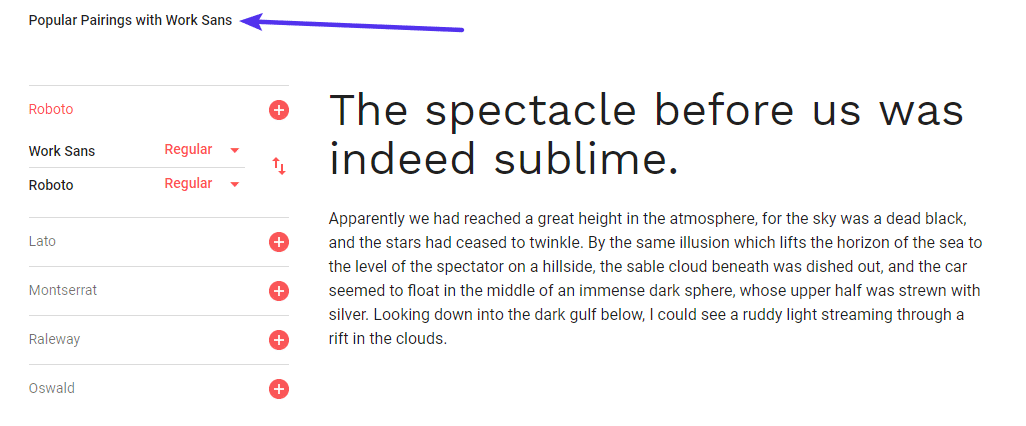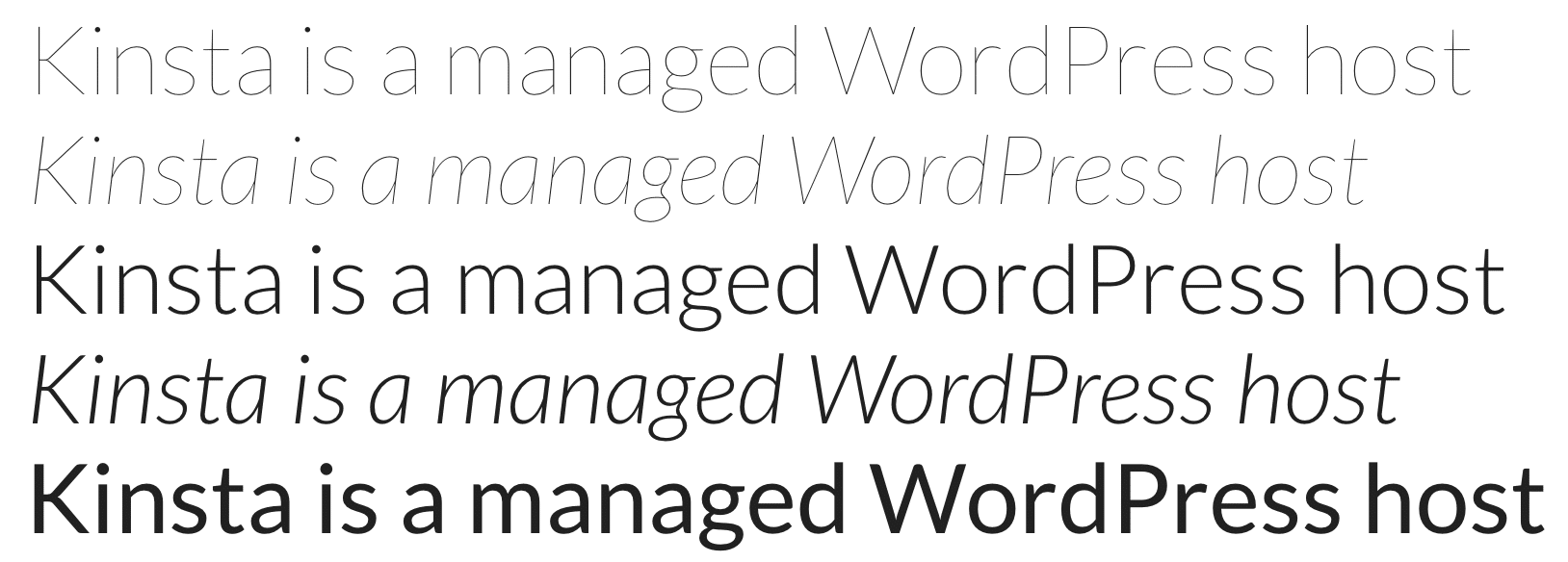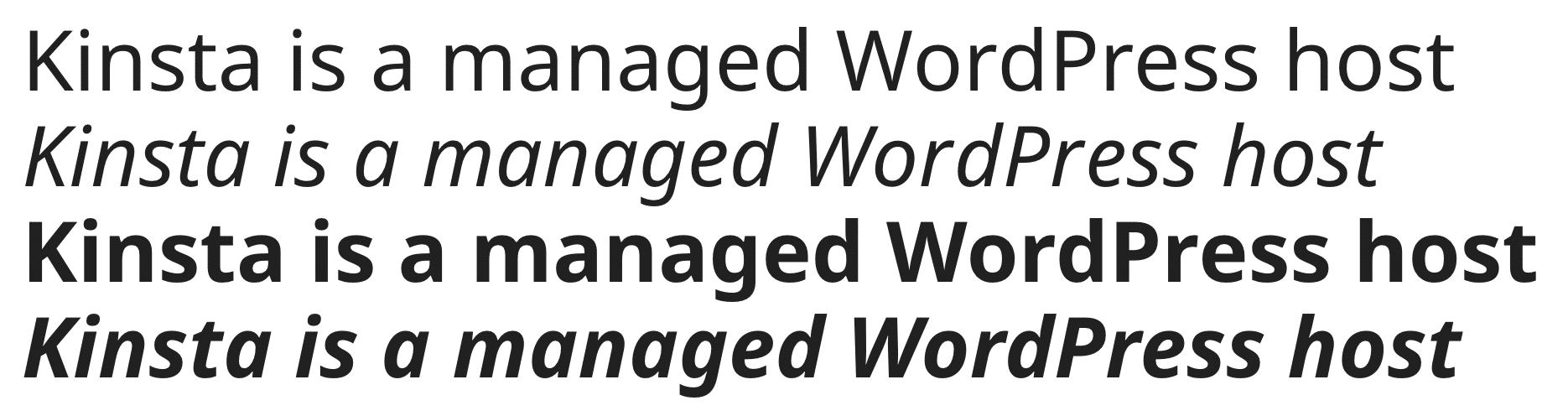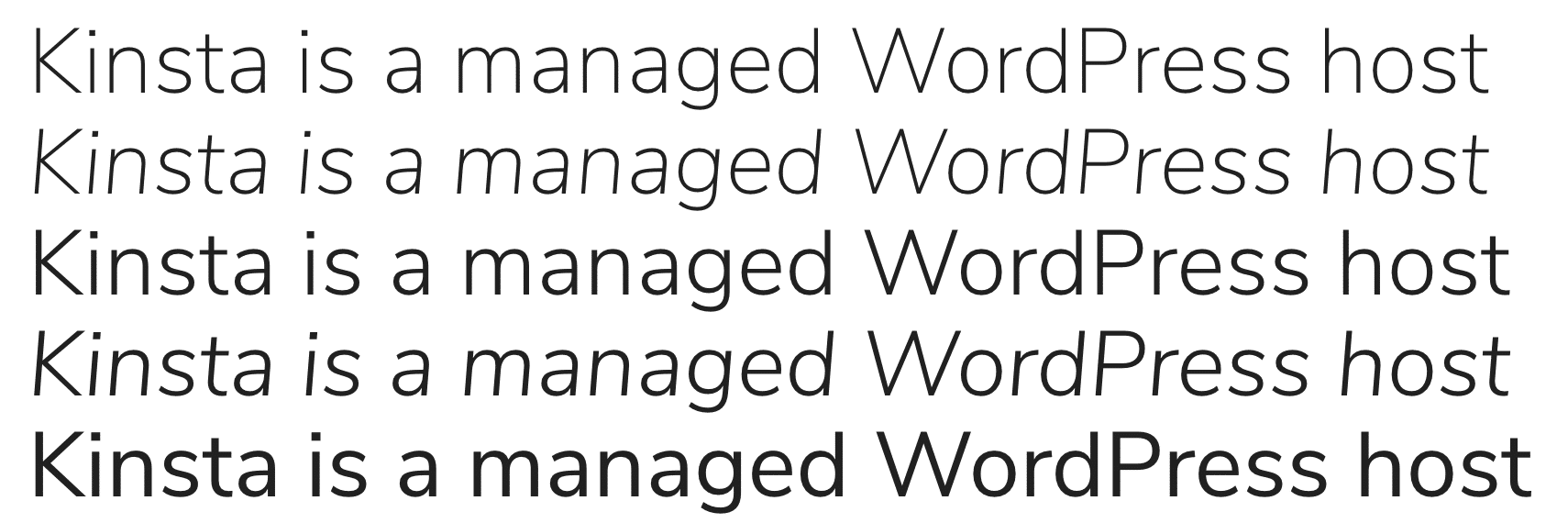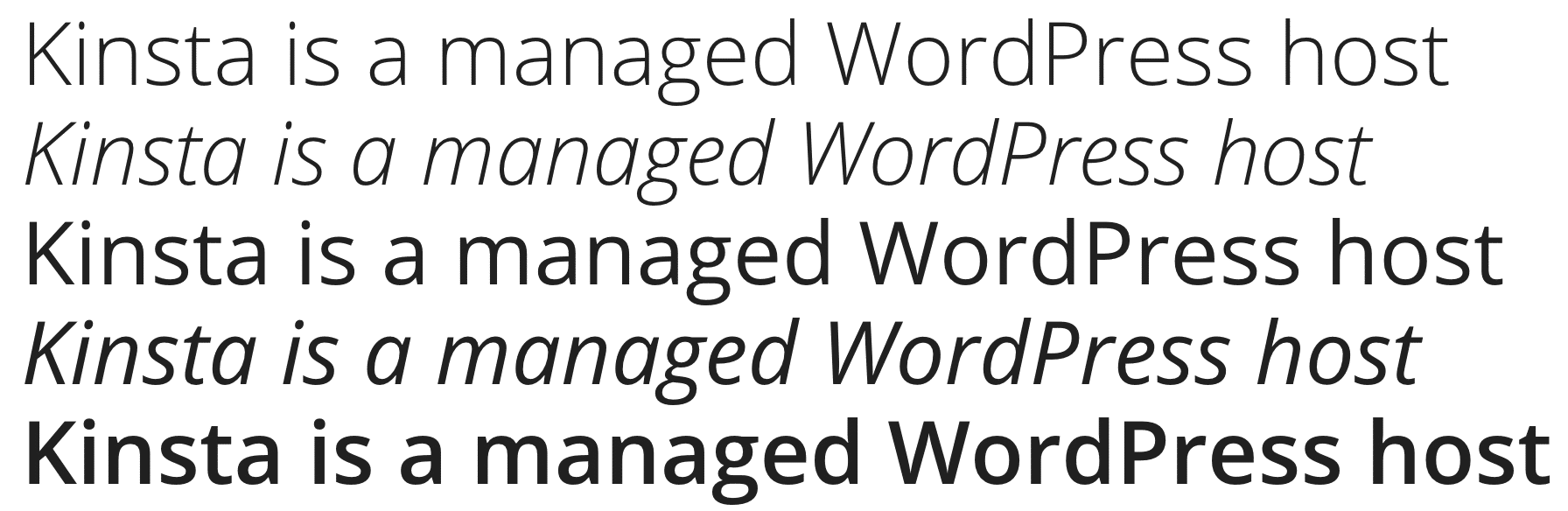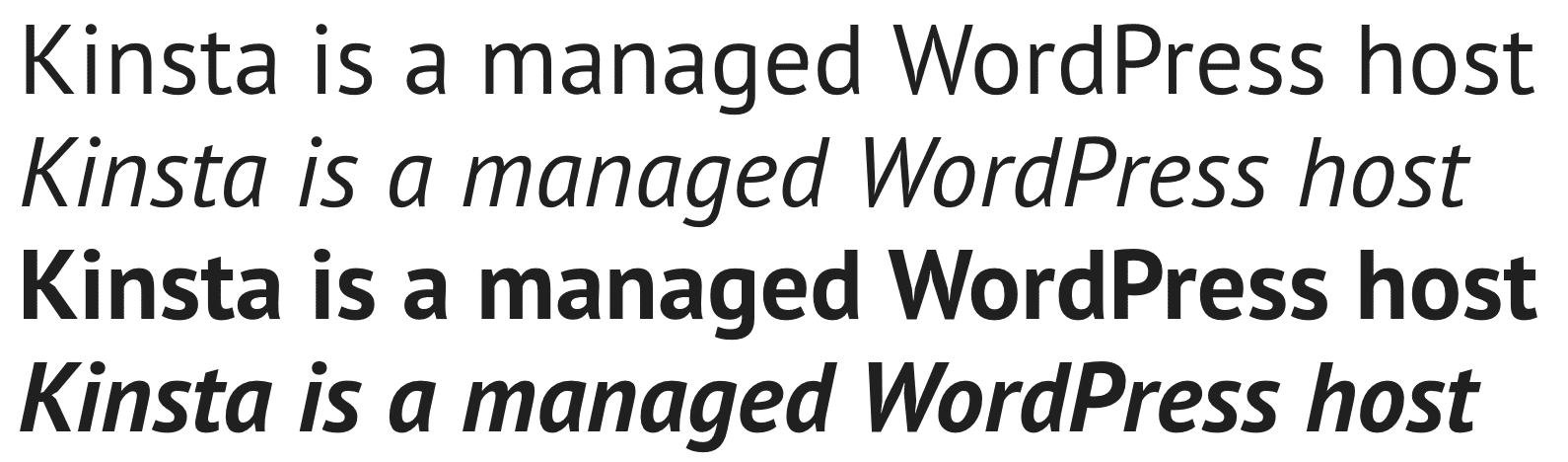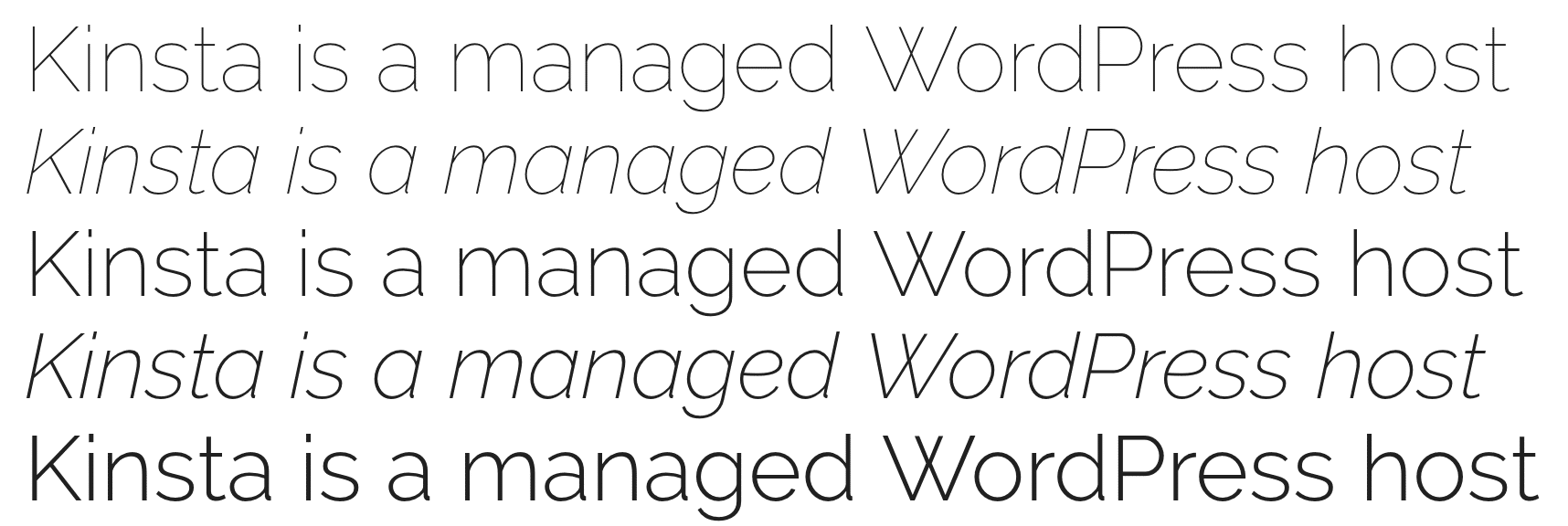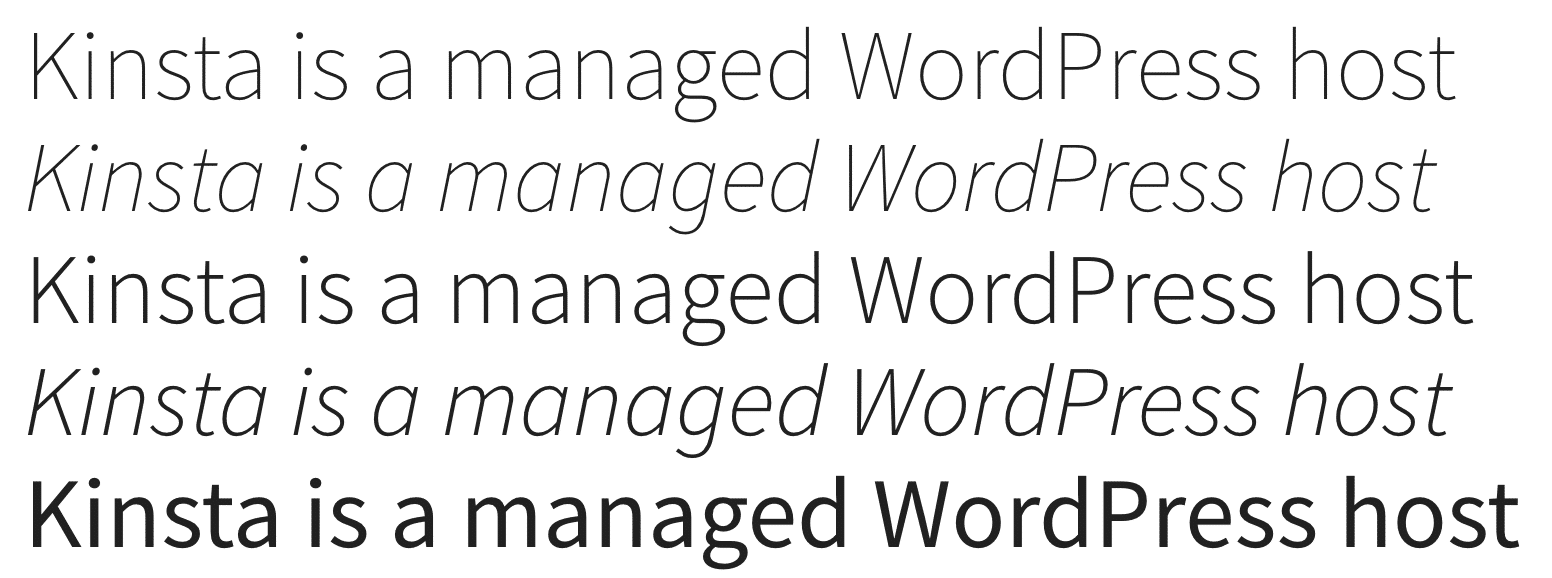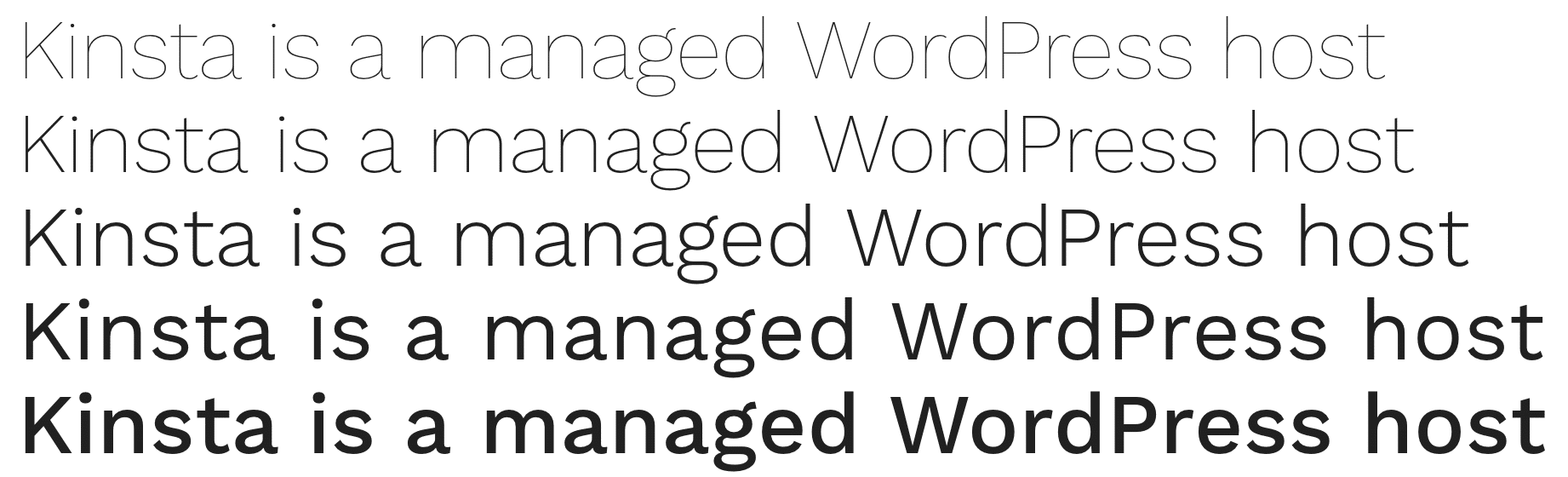
Il existe 1052 familles de polices Google différentes disponibles gratuitement (au moment de la rédaction de cet article). Cela fait beaucoup de choix ! Il n’est donc pas étonnant que vous ayez besoin d’aide pour trouver cette aiguille dans une botte de foin avec une liste des meilleures polices Google.
Nous l’avons trouvé pour vous, et nous partagerons également quelques bonnes pratiques pour l’utilisation des polices Google dans WordPress.
Le choix d’une police est plus qu’un simple choix esthétique : il peut avoir un effet considérable sur les taux de rebond et de conversion de votre site, surtout si vous choisissez une police difficile à lire. Il est donc préférable de prendre un peu de temps pour choisir la famille de polices Google idéale pour votre site web, plutôt que d’utiliser la première police venue.
Pourquoi utiliser Google Fonts?
Il existe des milliers de dépôts de polices sur Internet, alors qu’est-ce qui rend les polices Google si spéciales ?
Tout d’abord, c’est gratuit ! De plus, les polices Google sont gérées et distribuées par Google, ce qui signifie que leur sécurité est garantie. Bien sûr, il existe de nombreux sites web douteux où vous pouvez télécharger des polices gratuites, mais qui sait ce que vous risquez d’attraper avec ces fichiers ?
La qualité des polices sur ces sites web peut aussi parfois être douteuse.
Google a sélectionné plus d’un millier de polices de haute qualité. Si vous n’êtes pas un graphiste ayant un œil parfait pour la typographie, c’est un choix plus sûr.
Bien que les polices Google aient tendance à être simples et peut-être pas aussi voyantes que certaines polices payantes, elles sont certainement meilleures que les polices sécurisées pour le web qui sont préinstallées avec les principaux systèmes d’exploitation, les mêmes polices que tout le monde a vues des milliers de fois auparavant.
Ce qu’il faut rechercher dans une police Google
S’il y a une chose que vous devez apprendre lors de la conception d’un site web, c’est comment choisir une police Google adaptée à votre projet. Une bonne typographie peut faire ou défaire votre site.
Ce détail peut sembler insignifiant, mais il peut faire la différence entre une personne qui quitte votre site prématurément et une personne qui y reste pour devenir un lecteur ou un client fidèle.
Le choix de la bonne police est une tâche que les graphistes passent des années à maîtriser, mais en gardant quelques principes à l’esprit, vous pouvez choisir une belle police pour votre site web.
- Correspondance avec votre marque : C’est peut-être l’aspect le plus important. Les meilleurs sites web ont une police qui met en valeur leur personnalité tout en étant lisible et en s’intégrant au design actuel. Par exemple, Apple et Iron Maiden utilisent des polices très différentes, mais elles correspondent toutes deux à leur marque.
- Lisibilité : Le deuxième principe le plus crucial est la lisibilité. Une police fantaisiste ou grunge peut certainement convenir à votre marque, mais si vos visiteurs ne peuvent pas la lire, ils s’empresseront de partir. Par conséquent, vos polices doivent être professionnelles et lisibles.
- Classification de police : Bien qu’il existe des centaines de façons de classer une police, voici les cinq principaux types de polices : serif, sans-serif, script, monospace et décoratif. Une police de type script ou serif est synonyme d’élégance, tandis que les polices monospaces sont populaires sur les sites techniques. La connaissance de ces classifications vous donnera un meilleur point de départ dans votre recherche.
- Police d’affichage ou police de corps : Les polices d’affichage sont destinées aux grands formats, aux en-têtes ou aux projets d’impression. Elles peuvent se permettre d’être moins lisibles dans l’intérêt d’un design unique. La directive principale des polices de corps est la lisibilité, car elles constitueront la majeure partie de votre site.